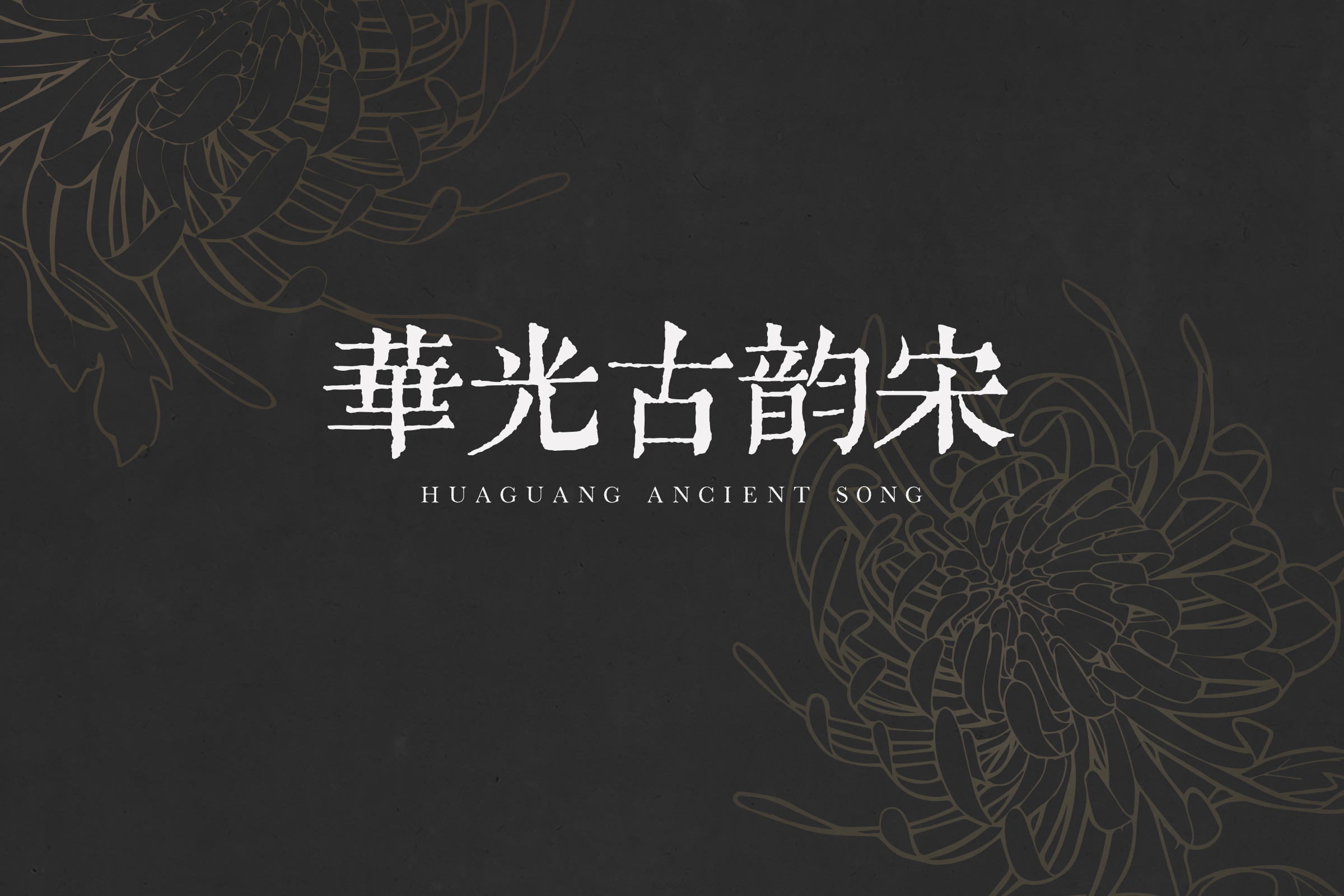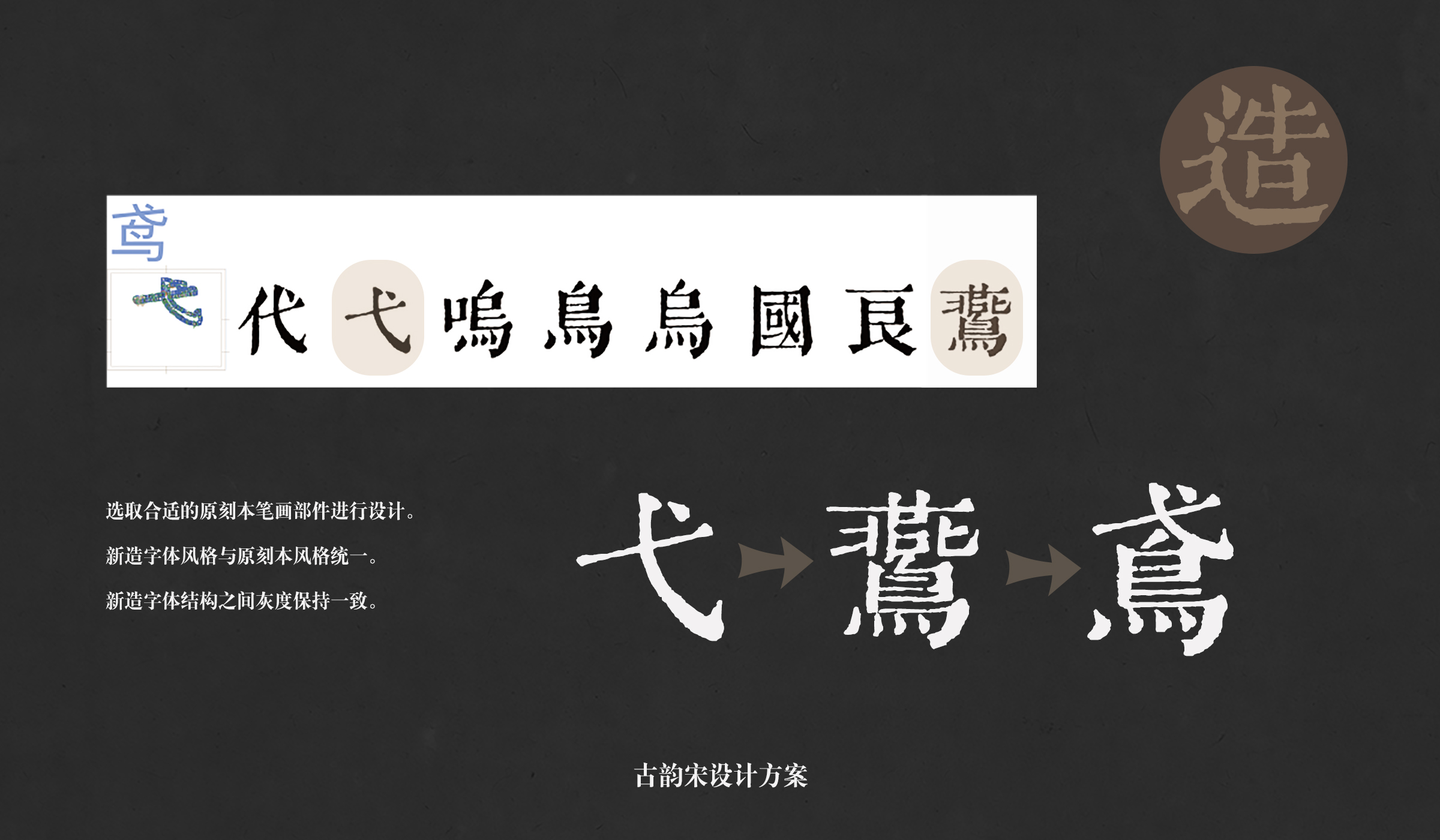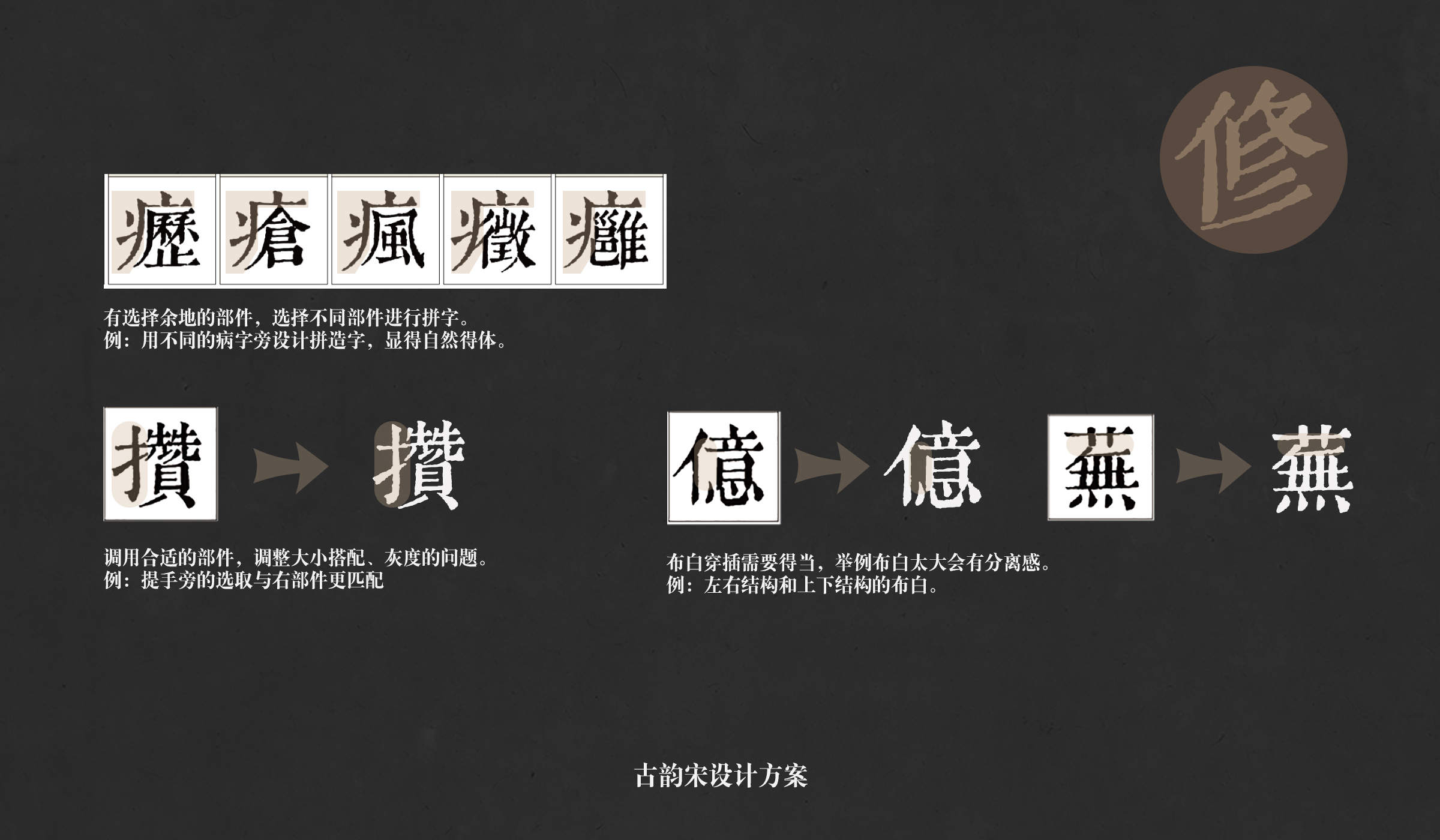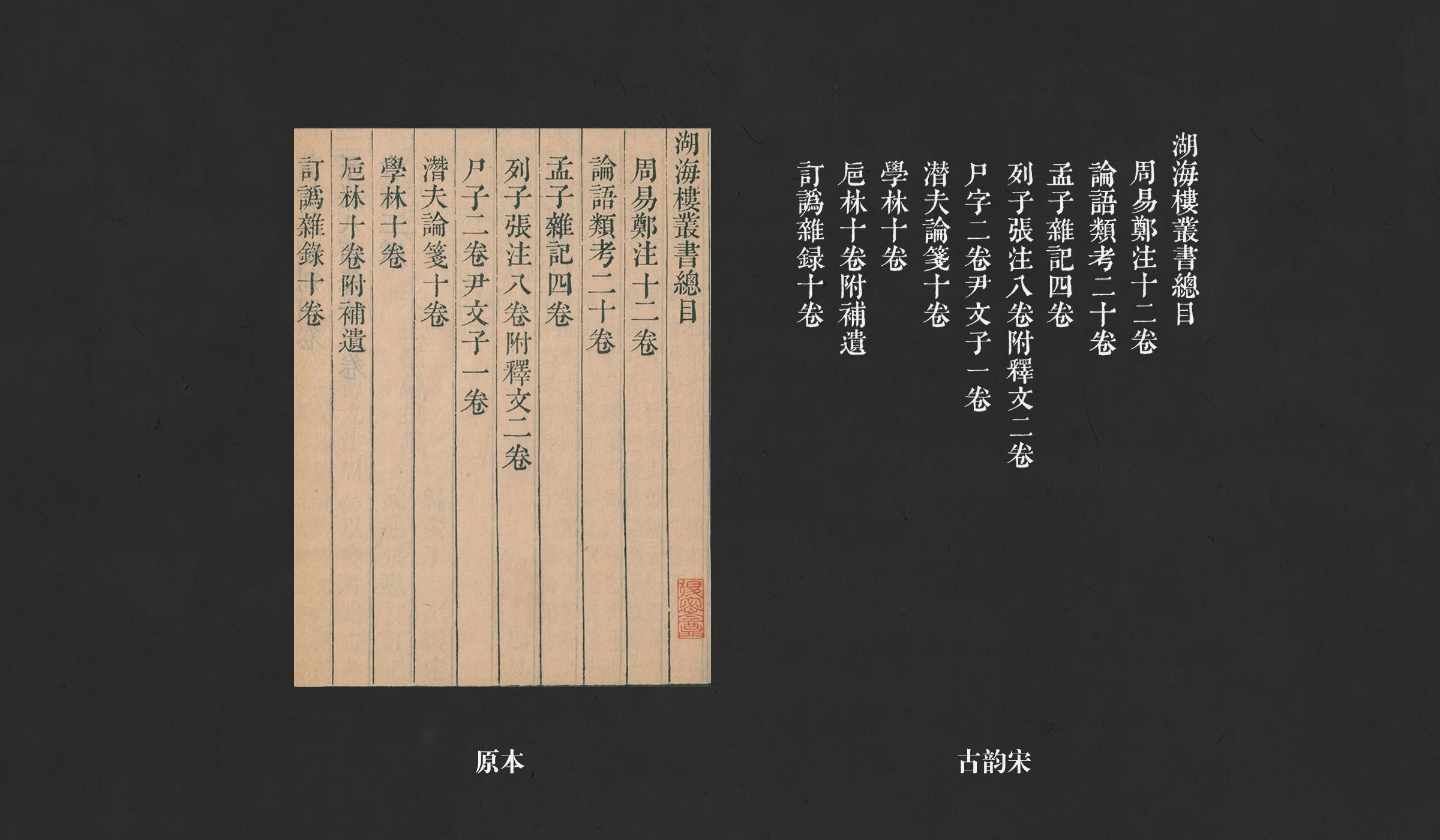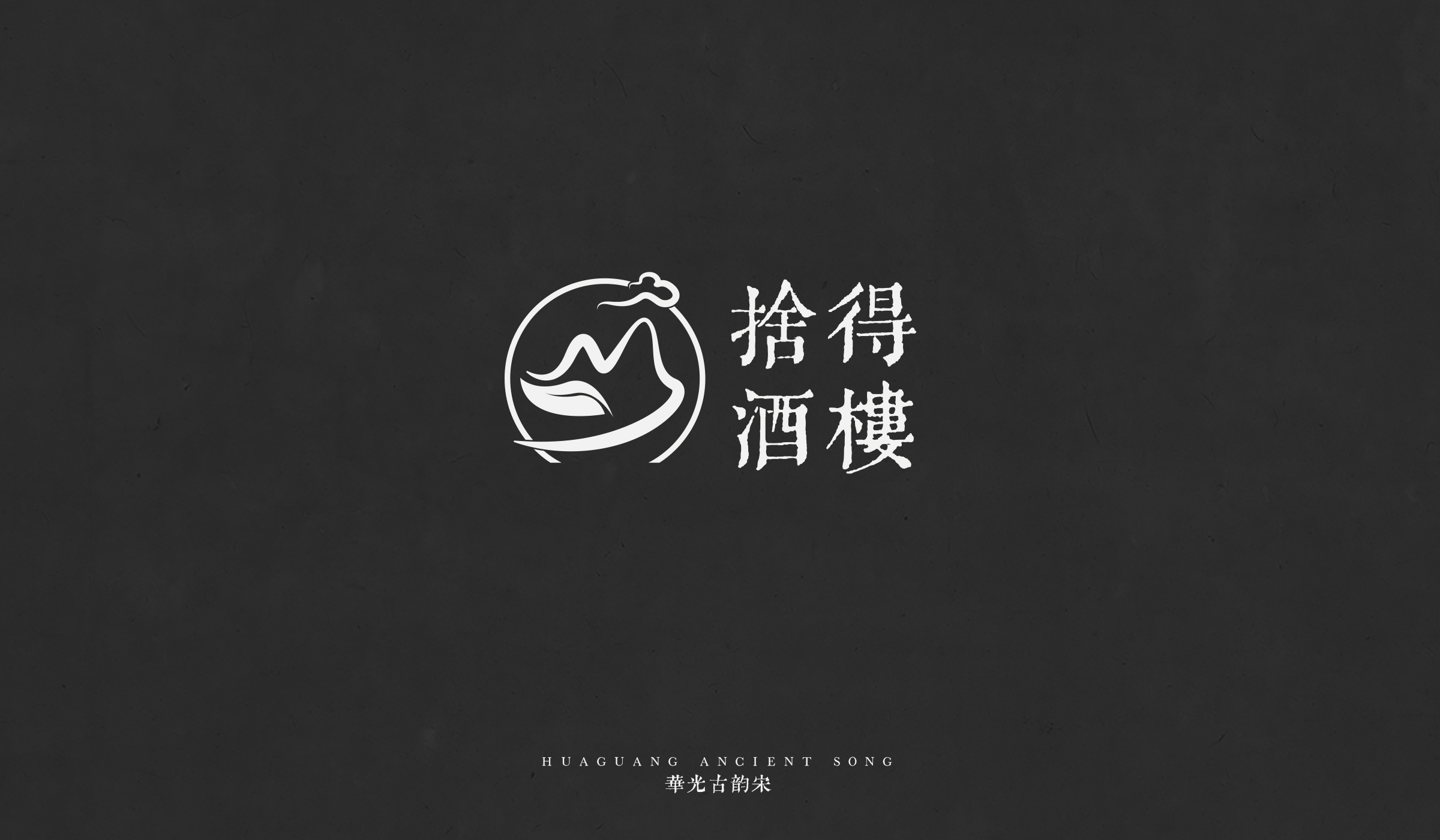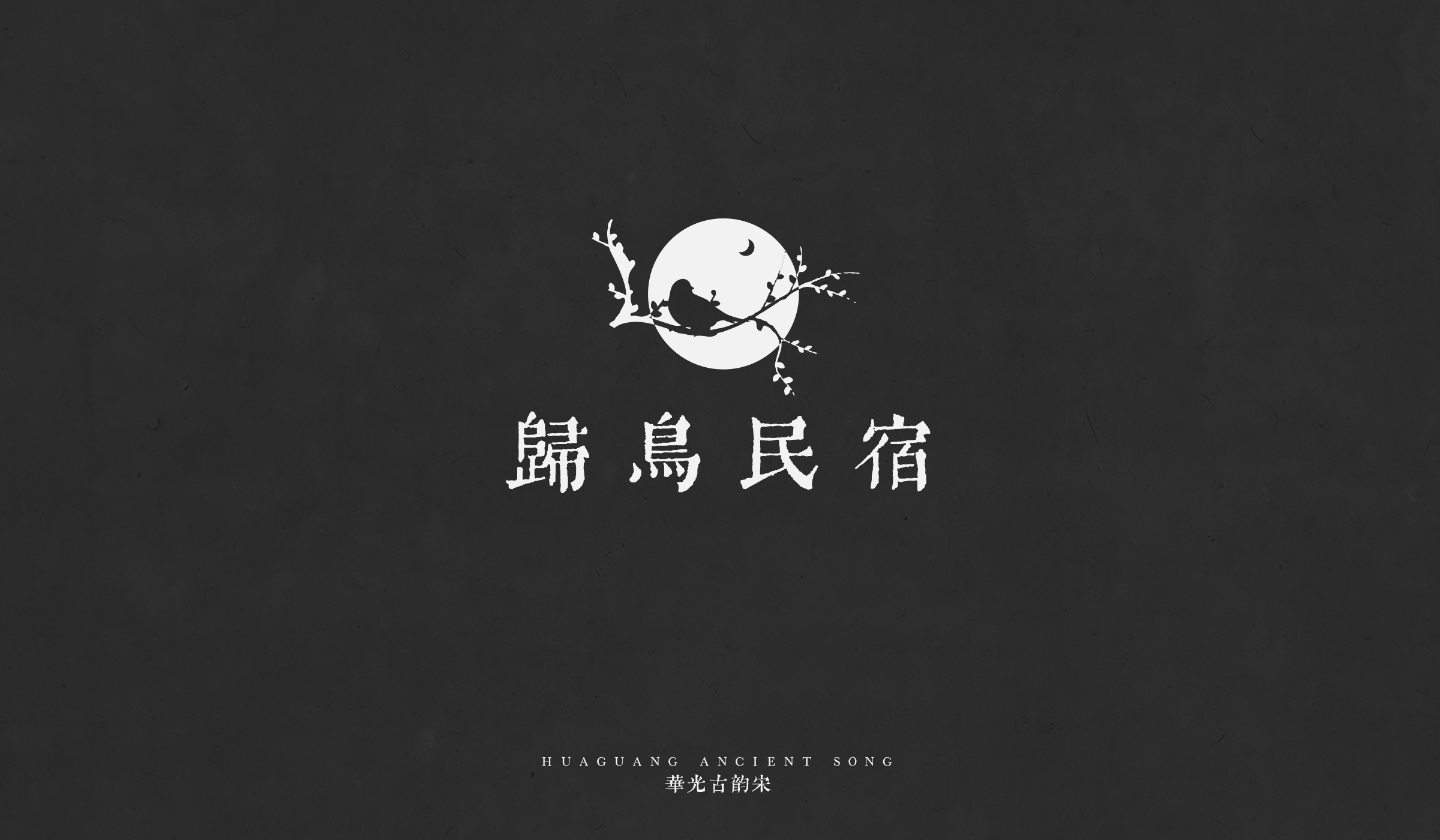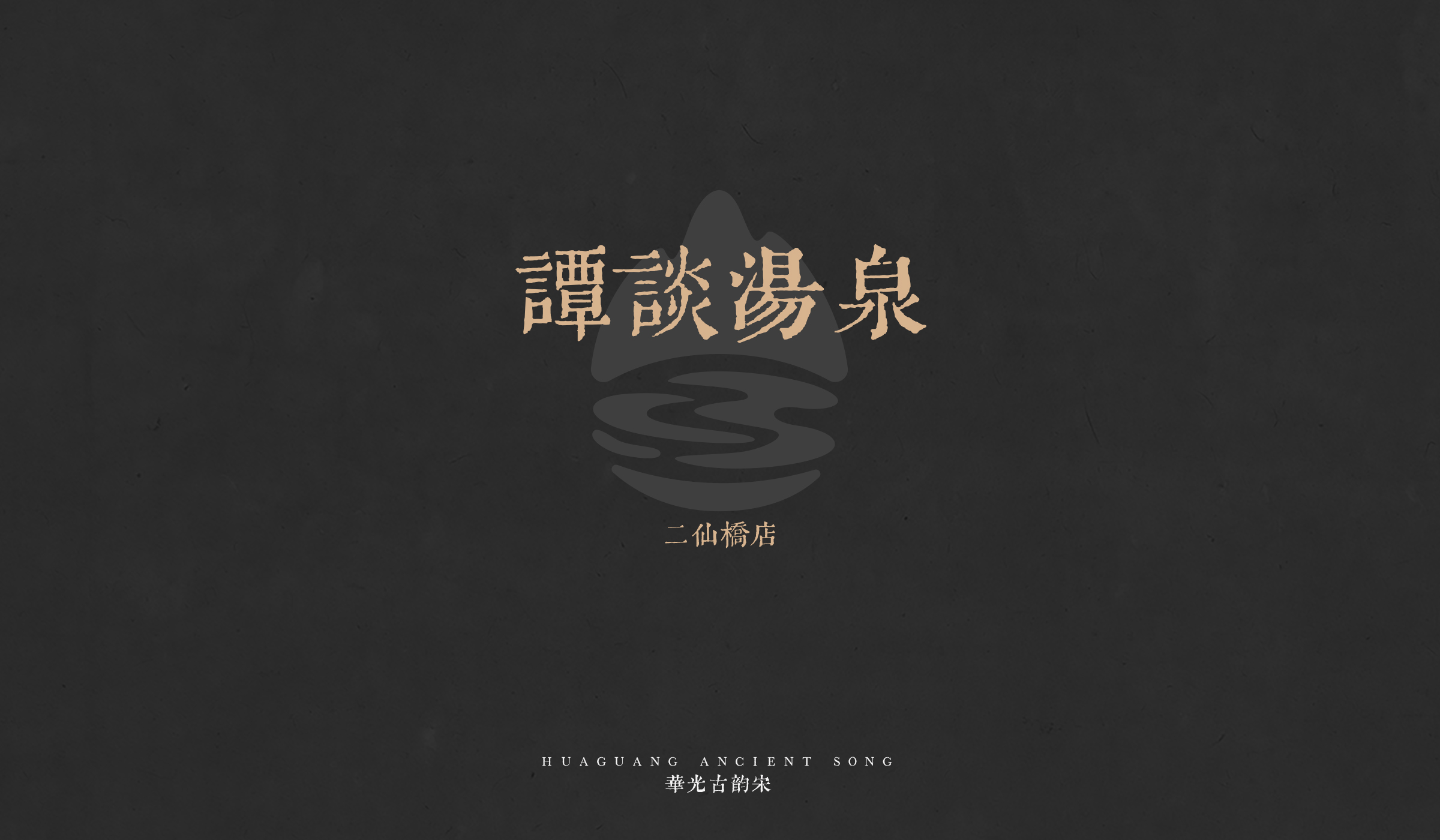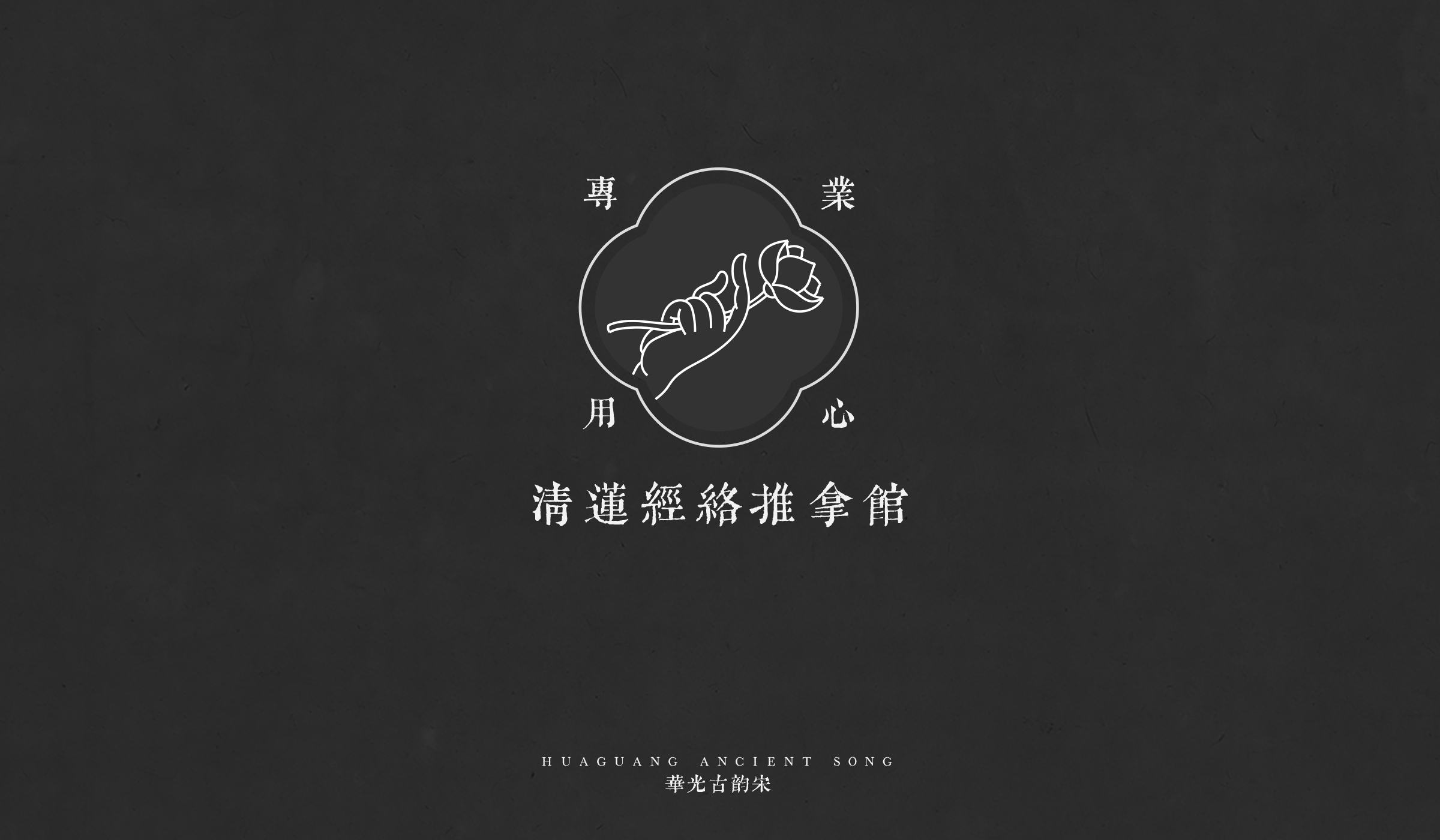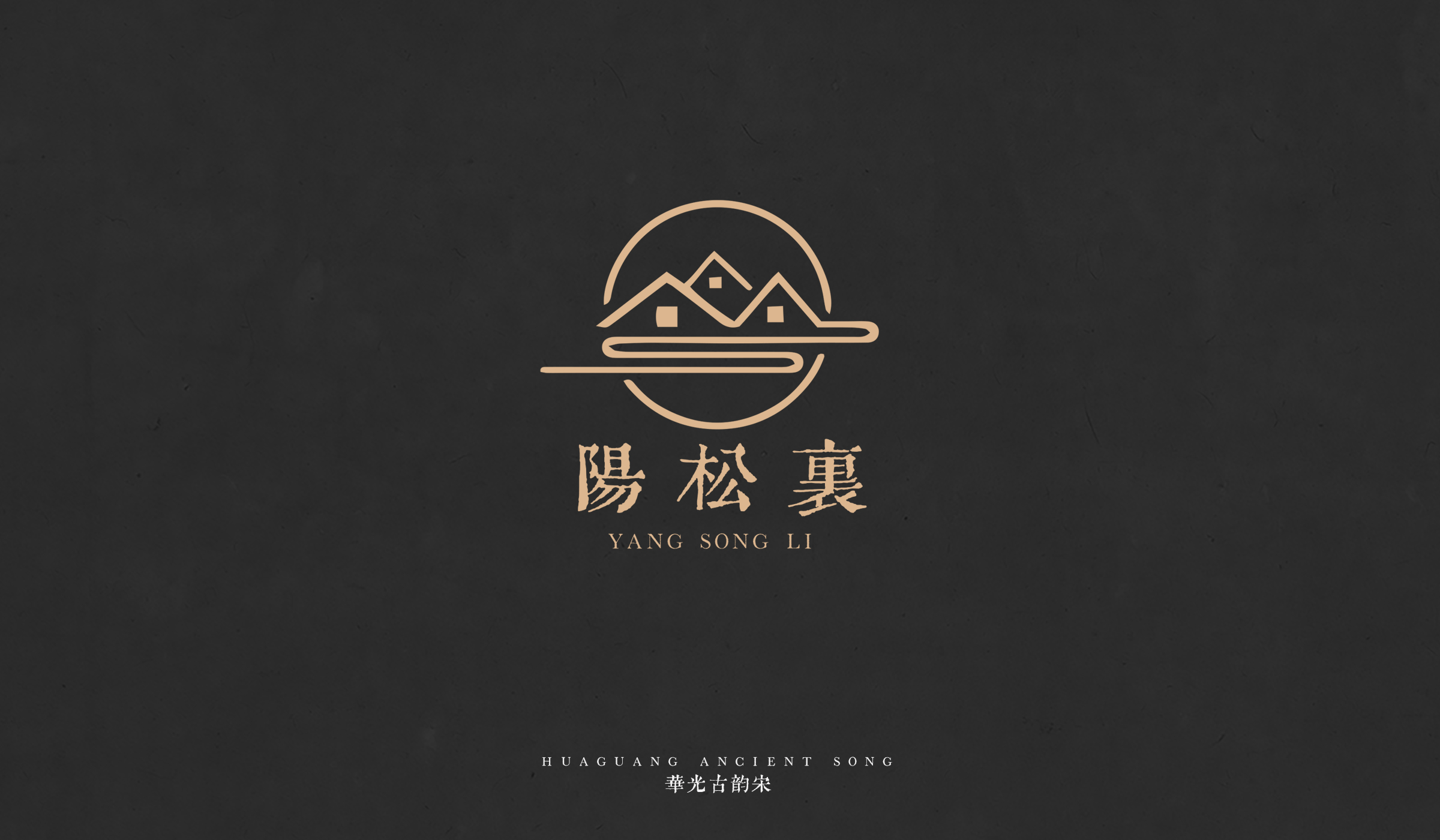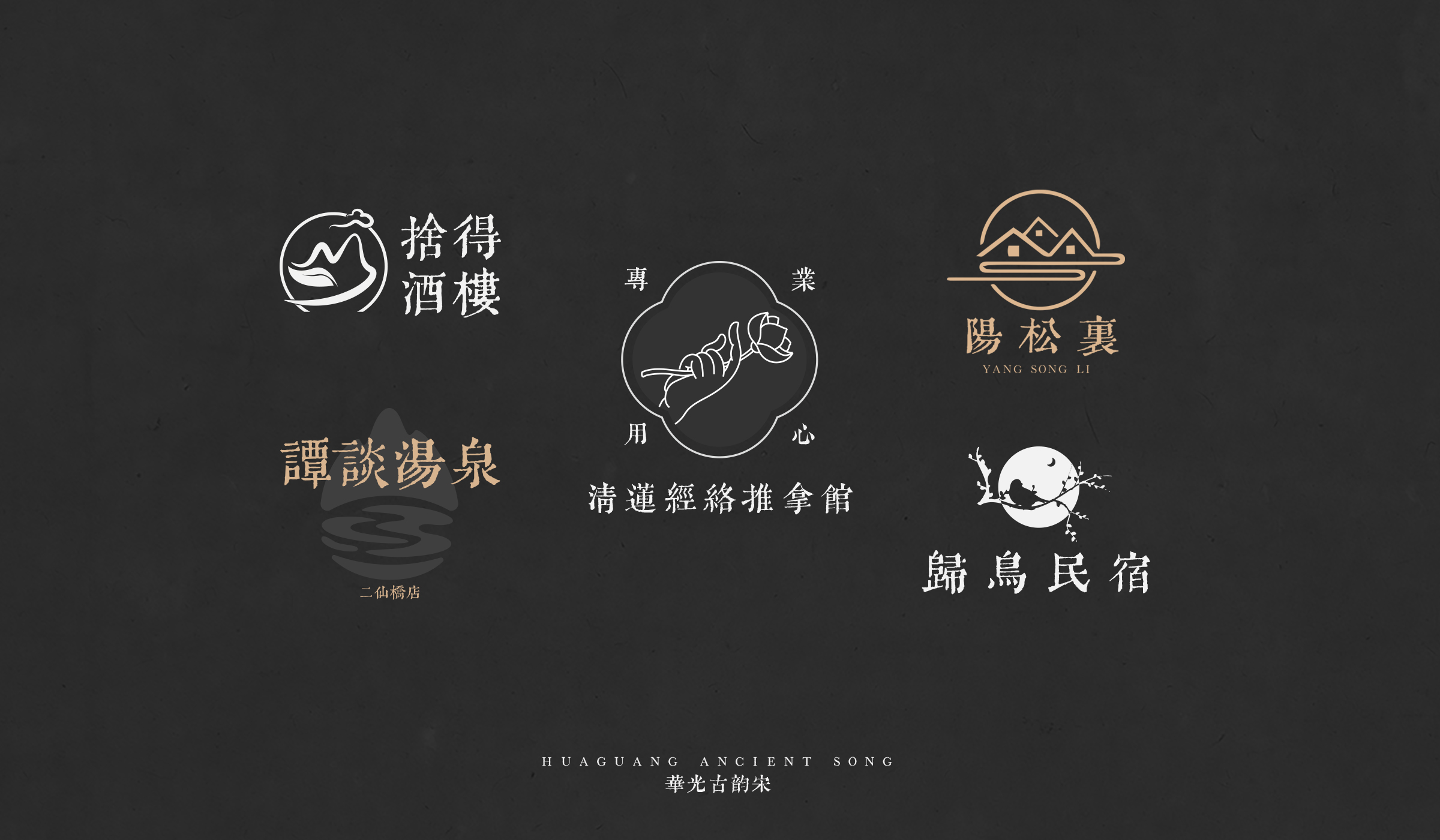
华光古韵宋
华光古韵宋取材自清代嘉庆年间《湖海楼丛书》中的刻本字体,在保留原刻本形韵的基础上,设计完成汉字字符7113字,以满足日常用字需求。字形清秀挺拔,结构稳重,笔形横细竖粗,撇长而精,捺粗而拙,体现出古拙感和文艺感、雕刻感。通过优化字形结构及笔形,使辨识度得到了加强。为展现出古朴的风格,全套字库为繁体字形。 清刻风格的古韵宋适用于品牌设计、广告设计和具有人文感、文艺感的场景等。 刻本字库设计是与时空的对话,古时的工匠精神值得今天每个字体设计者学习和膜拜。每个字背后都有一个故事,每个字同样也代表着整个字库,正所谓:"一花一世界,一叶一菩提"。